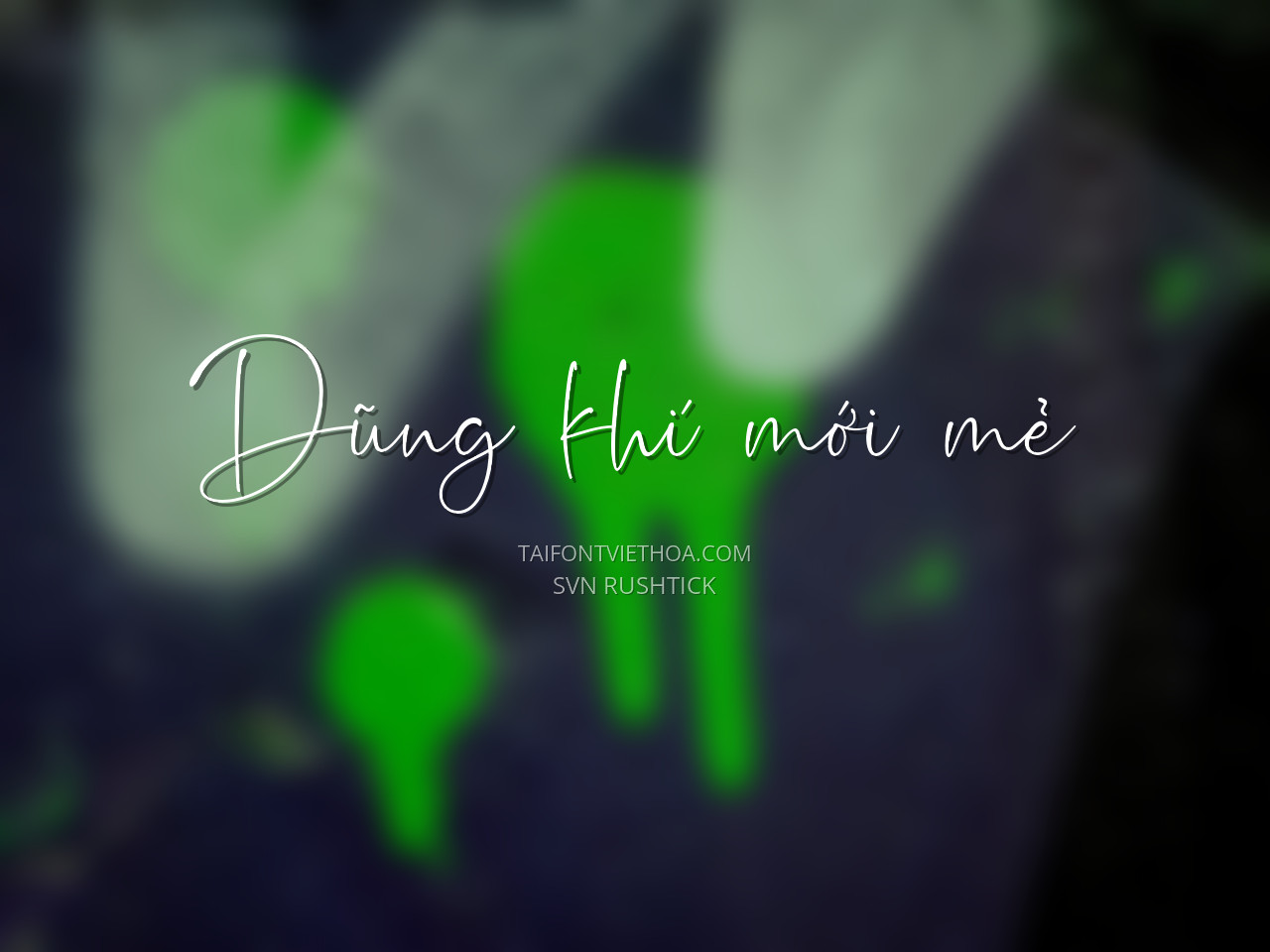
Font việt hóa SVN Rushtick
Giới thiệu về font SVN Rushtick – Phong cách viết tay tự nhiên, năng động và cá tính
SVN Rushtick là phiên bản Việt hóa của font Rushtick – một kiểu chữ handwritten mang phong cách tự do, phóng khoáng và có nét năng động. Font lấy cảm hứng từ những nét viết tay nhanh, thoải mái, giúp tạo nên sự chân thực và gần gũi trong các thiết kế. Rushtick thường được ứng dụng trong các dự án sáng tạo, truyền tải thông điệp cá nhân hoặc phong cách trẻ trung, hiện đại.
Phiên bản Việt hóa SVN Rushtick được Taifontviethoa.comchăm chút kỹ lưỡng, hỗ trợ đầy đủ dấu tiếng Việt và hơn 60 ngôn ngữ khác, giúp giữ nguyên nét đặc trưng mềm mại và tự nhiên của bản gốc. Font phù hợp cho những thiết kế cần sự biểu cảm cao và phong cách độc đáo.
Thiết kế viết tay uyển chuyển – Lý tưởng cho thiết kế sáng tạo và thương hiệu cá nhân
SVN Rushtick có các nét chữ không đều, độ nghiêng vừa phải, kết hợp các ligature độc đáo tạo nên cảm giác chuyển động linh hoạt và tự nhiên. Các ký tự mang tính thủ công cao, giúp truyền tải sự chân thật và biểu cảm cá nhân. Font rất thích hợp để sử dụng trong logo, thiệp mời, quote, bìa sách hoặc các sản phẩm sáng tạo mang dấu ấn riêng.
Ứng dụng lý tưởng: thiết kế thiệp cưới, lời chúc, logo thương hiệu cá nhân, quote nghệ thuật, poster sáng tạo và các dự án đòi hỏi phong cách viết tay tự do. Ngành nghề phù hợp: nghệ thuật, thiết kế, truyền thông sáng tạo, thời trang, mỹ phẩm handmade và các thương hiệu cá tính, trẻ trung.